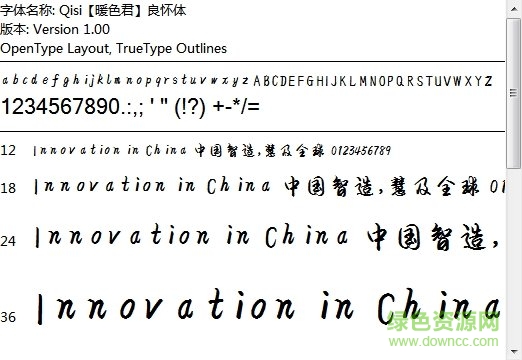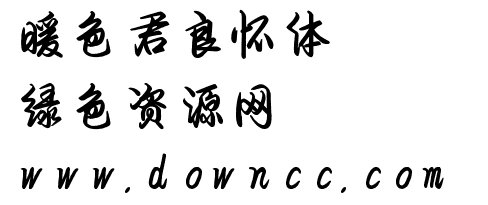
良懷體字體
良懷體是一款與良懷行書字體不同的特色手寫字體,規(guī)整了字體的設(shè)計(jì)風(fēng)格,使其更顯飄逸娟秀,收緊了結(jié)構(gòu)讓其更加溫婉,如果你喜歡就來綠色資源網(wǎng)試試吧!
良懷體由來
良懷體出自奇思暖色君補(bǔ)充分享的字體,良懷體很適合用于練字模仿的對(duì)象,整個(gè)字體效果美觀又耐看,是一款用于藝術(shù)設(shè)計(jì)方面的字體!
良懷體完整版
良懷體與良懷性書體在風(fēng)格上十分接近,而良懷體在暖色君的補(bǔ)充基礎(chǔ)上,完善了字庫,讓字跡更顯毛筆書法的飄逸格調(diào),十分喜人!